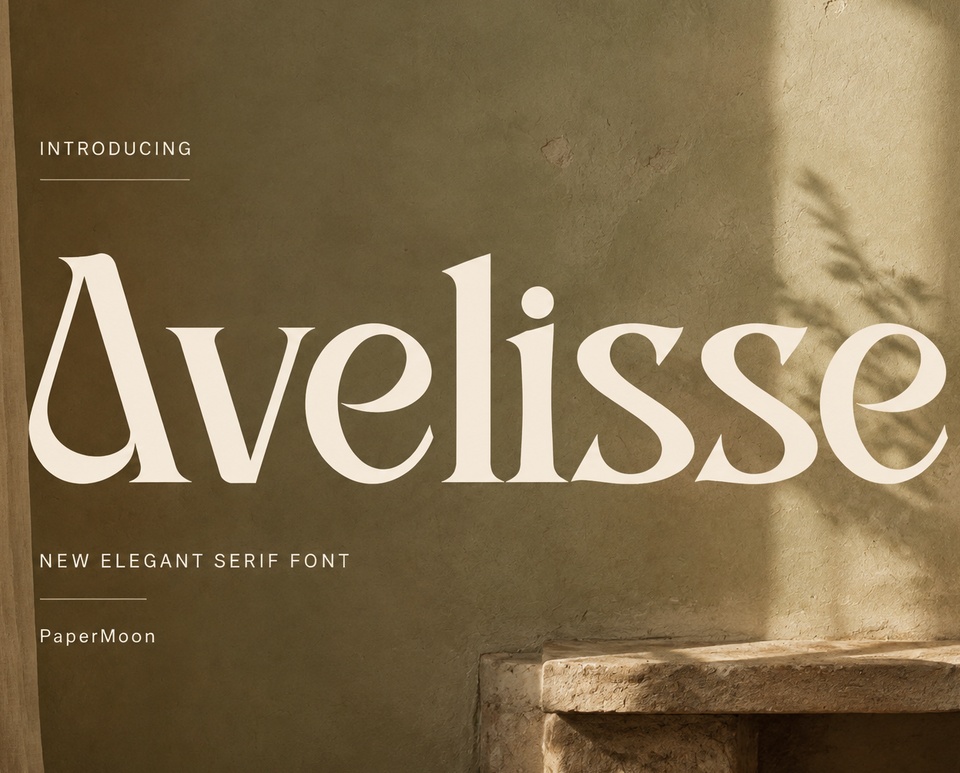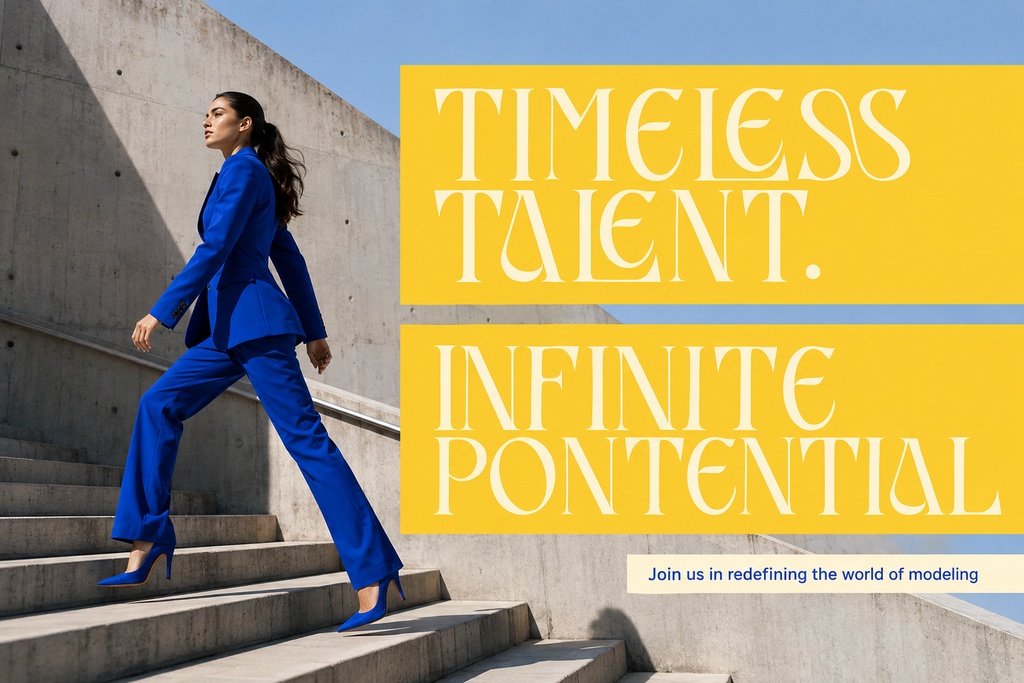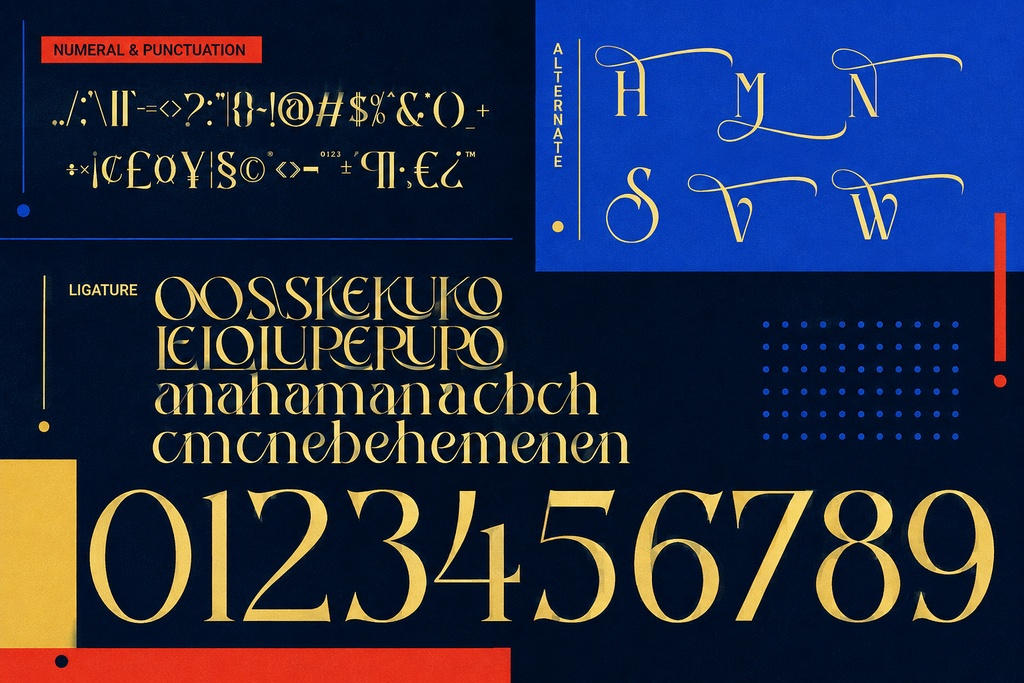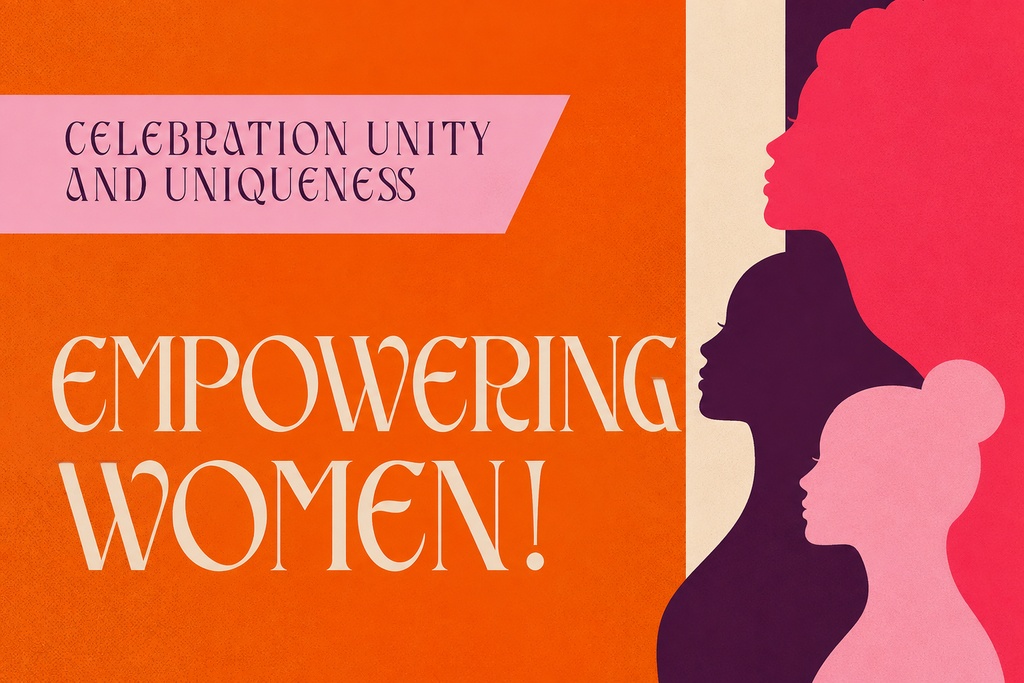
Avelisse — ブランディング&エディトリアル向け、モダンでラグジュアリーなセリフフォント
**Avelisse(アヴェリス)**は、高級ブランド、エディトリアルデザイン、高級パッケージ、洗練されたビジュアルアイデンティティのために作られた、エレガントでモダンなラグジュアリー・セリフフォントです。 シャープで美しいセリフ、優雅な曲線、洗練されたコントラストが、上質で洗練されたエディトリアルな雰囲気を演出します。高級感がありながら冷たい印象にならない、信頼性の高いデザインフォントです。 ロゴデザイン、ブランドアイデンティティ、ファッションやビューティー関連のキャンペーン、雑誌・エディトリアルデザイン、ウェディング招待状、イベント用ステーショナリー、高級感のあるウェブサイトのヘッダー、SNS用グラフィックなど、幅広い用途に適しています。 ### ファイル形式 Avelisseには、**Regular(レギュラー)1ウェイト**が収録されており、以下の4つのフォーマットで提供されます。 * OTF * TTF * WOFF * WOFF2 229~230のグリフを収録し、A~Z、a~z、数字、標準的な句読点を含む**Basic Latin(基本ラテン文字)**に対応しています。 デスクトップや印刷物で使用する場合はOTFまたはTTFを、適切なライセンスのもとでウェブサイトに使用する場合はWOFFまたはWOFF2をご利用ください。 Adobe Photoshop、Illustrator、InDesignなどのOpenType対応アプリケーションをはじめ、Figma、Canva、Affinity、Procreate、Microsoft Wordなど、インストールされたデスクトップフォントに対応するさまざまなソフトウェアで使用できます。 ### 主な特徴 **豊富なカスタムリガチャ** OO、SS、KE、KU、KO、LE、LO、LU、RU、RO、REなどのカスタムリガチャに加え、ab、ah、am、an、cb、ch、cm、cn、eb、eh、em、enなどの小文字向けの組み合わせも収録しています。 これにより、見出しやタイトルで隣り合う文字がぶつかることなく、自然で美しい文字の流れを作り出します。 **スタイル代替文字** H、M、N、S、V、Wにはスタイル代替文字を用意しています。 ロゴやワードマーク、短いディスプレイテキストに使用することで、オーダーメイドのような個性的で洗練された仕上がりを演出できます。 **高度なOpenType機能** GPOSカーニングとGSUB機能に対応しており、文字間の組み合わせを細かく調整し、対応アプリケーション上で安定したOpenType動作を実現します。 ### おすすめの用途 * 高級ロゴデザイン・ブランドアイデンティティ * ファッション・ビューティー関連のパッケージ * 商品ラベル・ブティック向け印刷物 * エディトリアルデザイン・雑誌レイアウト * 見出し、プルクオート、マストヘッド * ウェディング招待状・Save the Date * イベント用ステーショナリー * 高級感のあるウェブサイトのヘッダー * SNS用グラフィック・ビジュアルコンテンツ ### 対応形式 OTF、TTF、WOFF、WOFF2の4形式を収録しています。 対応しているデザインソフトでは、**GlyphsパネルまたはOpenTypeパネル**からスタイル代替文字やリガチャにアクセスできます。 また、実際の制作・商用利用を開始する前に、収録されている文字セットが使用予定の言語要件を満たしているかをご確認ください。 ### ライセンス 推奨される標準ライセンスは**Cubebrush Commercial License**です。 このライセンスでは、商用デザイン制作、クライアント向けの完成作品、販売可能な完成アートワークなど、許可された用途でフォントを使用できます。通常、完成作品へのフォント作者のクレジット表記は必要ありません。 **Basic License**は、個人利用および非商用プロジェクトに限定されています。 ライセンスは、許可されたプロジェクトにおけるフォントソフトウェアの使用に適用されます。フォントファイルそのものを単独の商品として再販売、共有、配布することは禁止されています。 次のブランドアイデンティティ、パッケージデザイン、エディトリアル作品、ウェディングステーショナリーに、エレガントでモダン、そして洗練されたラグジュアリー感を加えたいなら、**Avelisse**をデザインツールにぜひ取り入れてみてください。